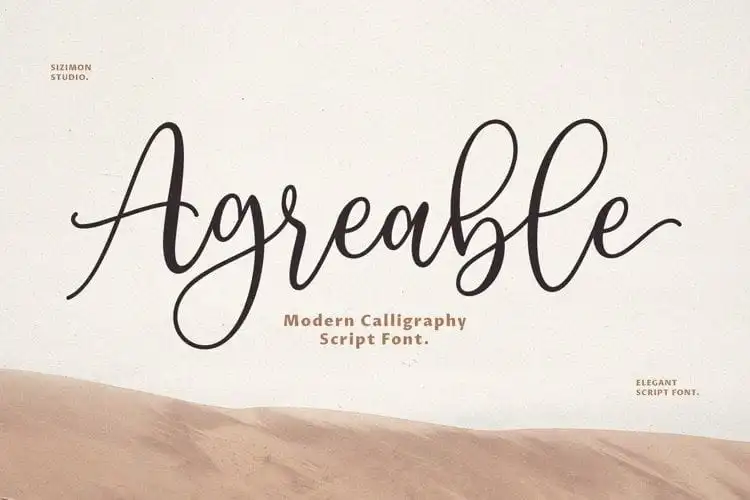
Agreable Script Font – Fonte Grátis
Agreable Script Font
A Agreable Script Font é uma solução elegante e moderna para seus esforços de design de marca. É perfeitamente projetada para criar tipo à mão feito a mão de maneira instantânea, oferecendo um fluxo livre com curvas suavemente rebondidas. A fonte agrega os elementos da elegância e do contemporaneirgama, tornando-se ideal para logotipos, citações impressas, convites, cartões, embalagens de produtos, cabeçalhos e quase qualquer elemento imaginável. Perfect para transformar seus ideais em realidade, a Agreable é uma fonte script perfeita para quem busca um toque refinado em sua próxima criação visual.